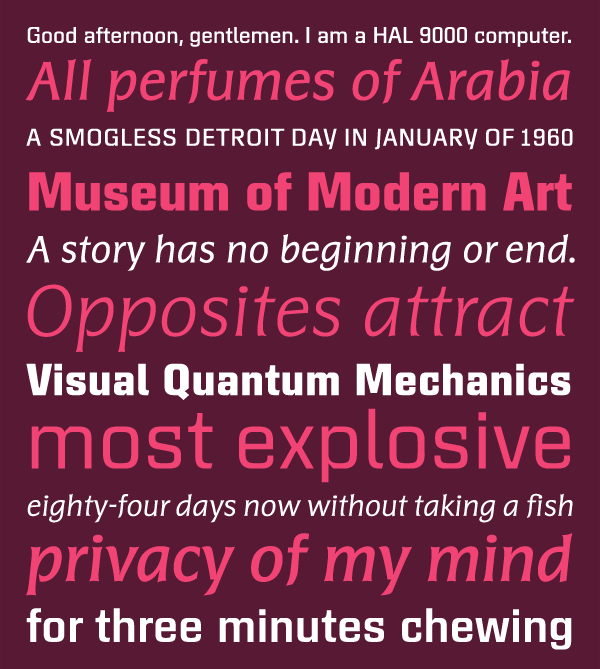
Rolls von Georg Salden
Die Schrift Rolls gehört zur Eurostil-Linie, die in den sechziger Jahren Aldo Novarese schuf. Alle eigentlich runden Buchstaben-Teile sind hier zu Geraden mit kurzen Eckkurven umgeformt worden. Sie gewinnen dadurch innen an Offenheit. Außen reiht sich aber Senkrechte an Senkrechte, was schon bei gebrochenen Schriften des Mittelalters schön ornamental und wenig lesefreundlich ankam. Bei der Rolls wurde mit Serifen anstelle von Eckkurven einigen Buchstaben mehr Eindeutigkeit gegeben. Sie gleicht damit eher einer Halb-Sanserif.
Besonders interessant ist die kalligrafische Kursive, die einen größtmöglichen Kontrast zur strengen und eckigen Aufrechten bildet. Aber gerade mit dieser zarten und schwungvollen kursiven Begleitung entfaltet Rolls ihren vollen Charme.